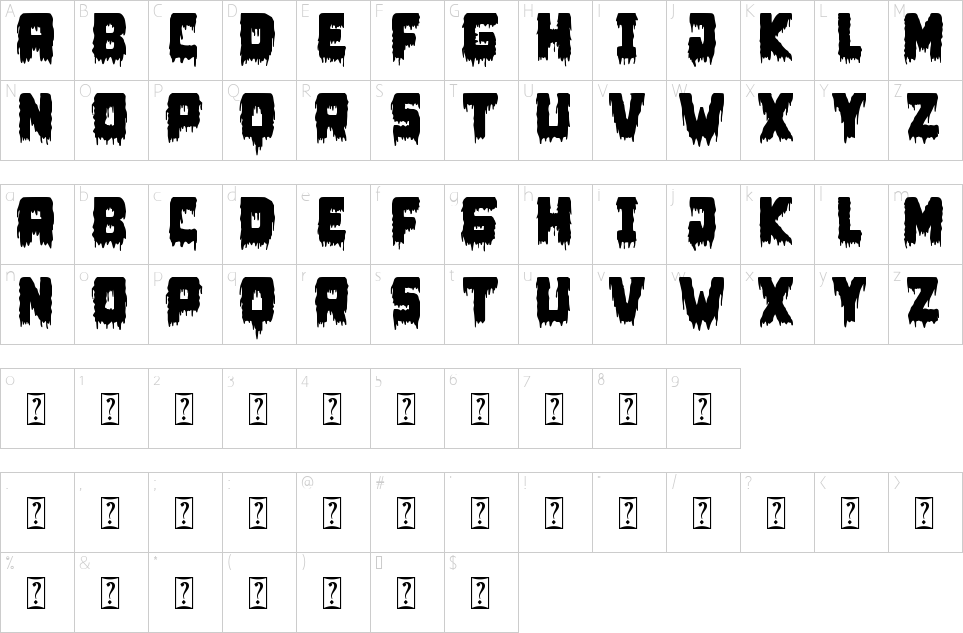
Zombie Mummy Font – Download Grátis
Esta página apresenta a Zombie Mummy Font, uma elegante e sobrenatural fonte que combina elementos macabros e surreais para criar um enredo único e memorável. Desenvolvida pelo designer Thomas Aradea, essa font é perfeita para qualquer projeto que precise de uma identidade visual inovadora e criativa. A Zombie Mummy Font se destaca entre as demais graças à sua aparência única e intrigante. Seu design surpreendentemente detalhado convida os criativos a explorar suas infinitas possibilidades, seja para aplicação em elementos visuais, logotipos ou qualquer material gráfico que exija uma solução de fonte inovadora. Com 1,680 downloads até o momento, já é evidente o quanto essa font se encaixa perfeitamente no nicho dos recursos gratuitos. Se você busca adicionar um toque singular e estiloso a seu trabalho gráfico, Zombie Mummy Font é uma escolha inteligente para adicionar à sua biblioteca de fontes. Não hesite em experimentar esta font única e inovadora para explorar novas maneiras de expressar suas ideias visuais.